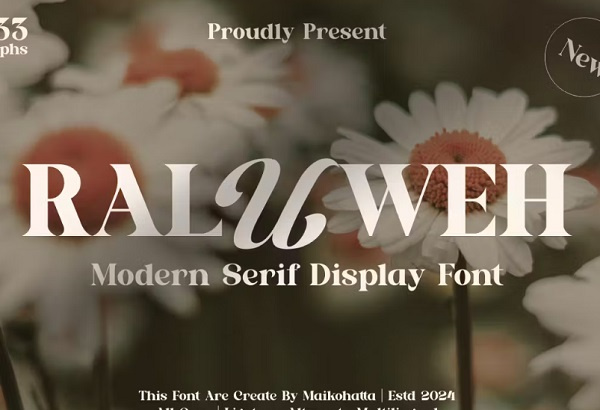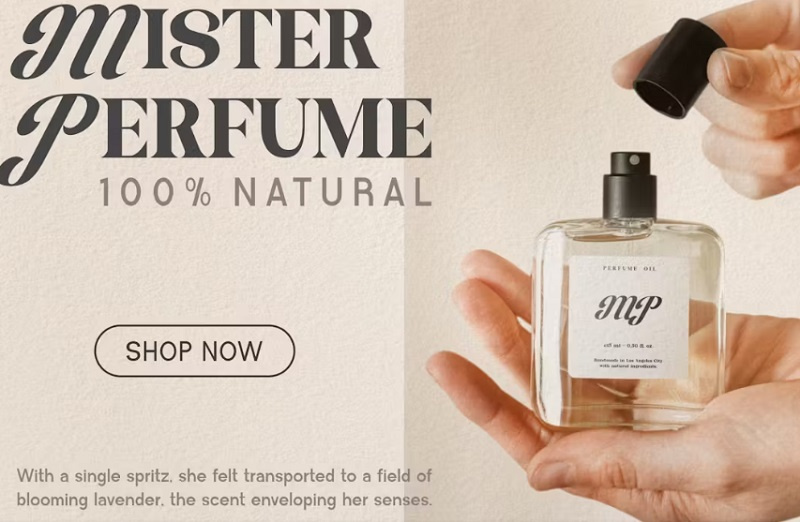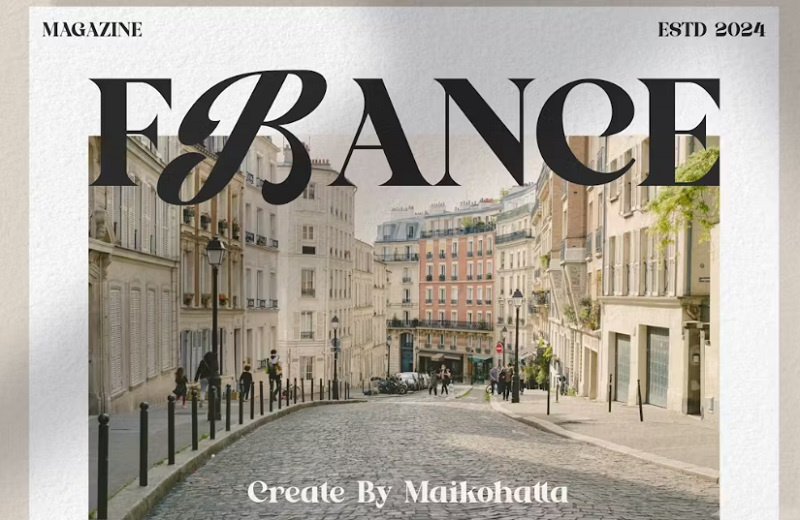
دانلود فونت انگلیسی Raluweh
فونت انگلیسی Raluweh
دانلود فونت انگلیسی Raluweh از جی اف ایکس دانلود. این فونت دارای نسبت متعادلی از ضخامت و ظرافت است که تصاویری جذاب و خوانا را ایجاد می کند. این فونت انگلیسی مناسب برای انواع طراحی ها، لوگو، سربرگ، تبلیغات، چاپ و ... می باشد. شامل فایل های otf و ttf است.
دانلود فونت زیبای Raluweh
✅ نام فونت انگلیسی: Raluweh - Modern Serif Display
✅ شامل حروف بزرگ و حروف کوچک
✅ چند زبانه